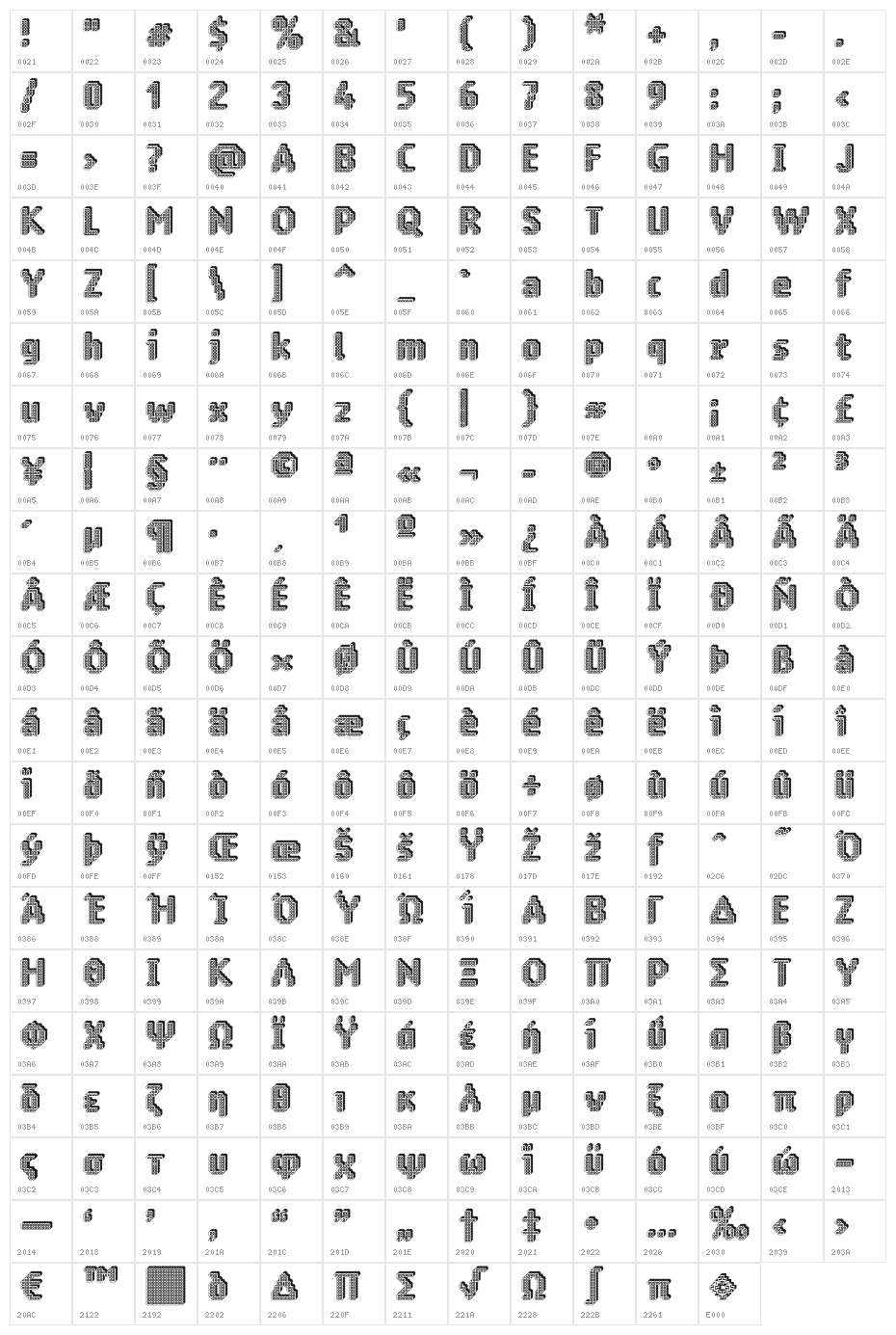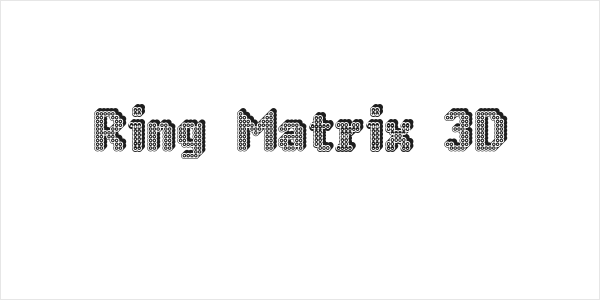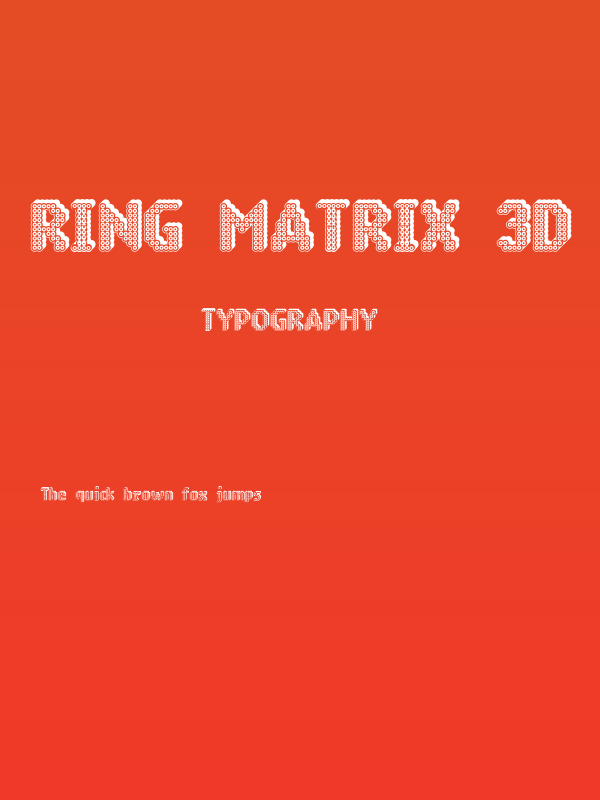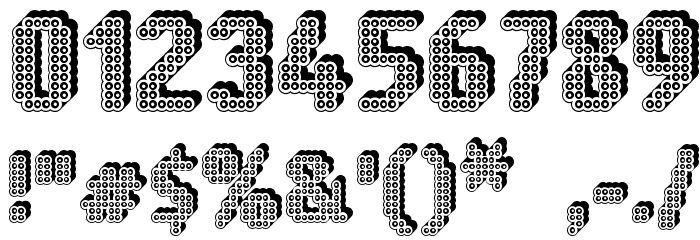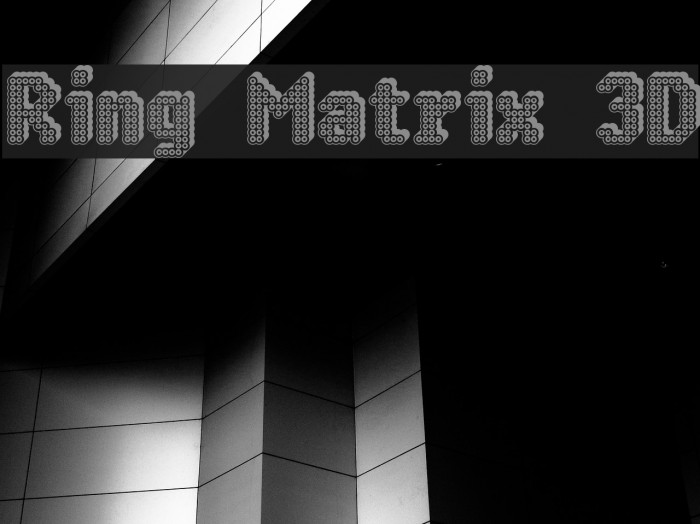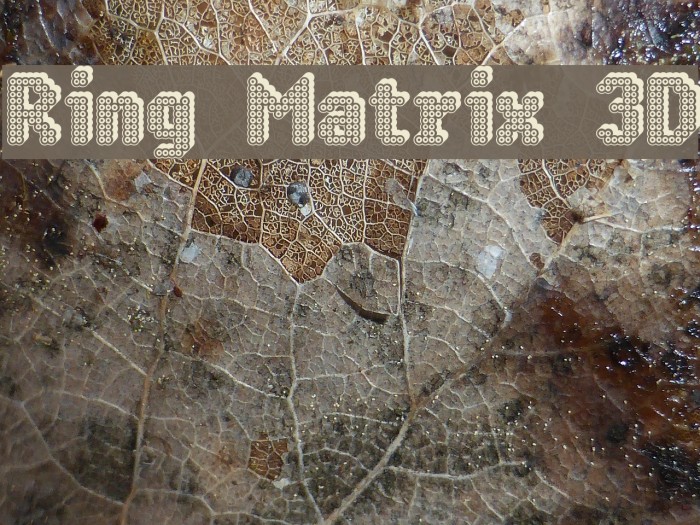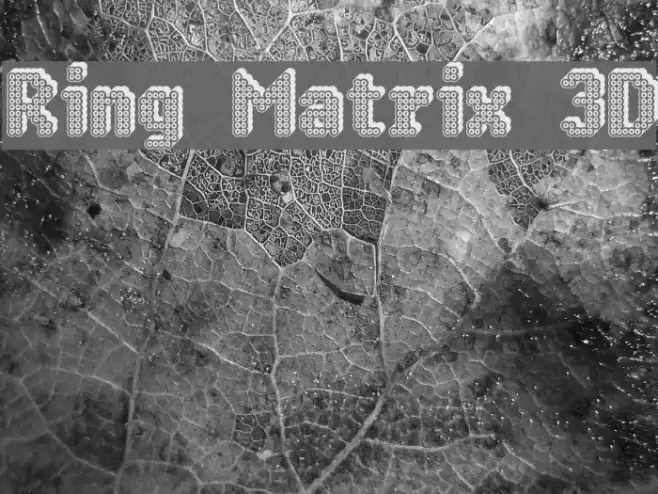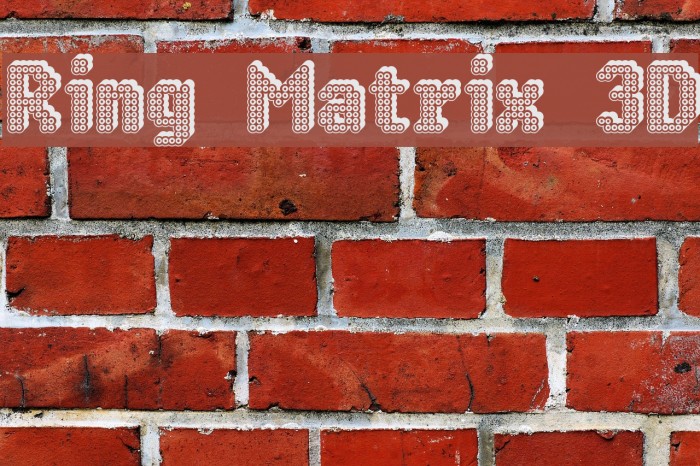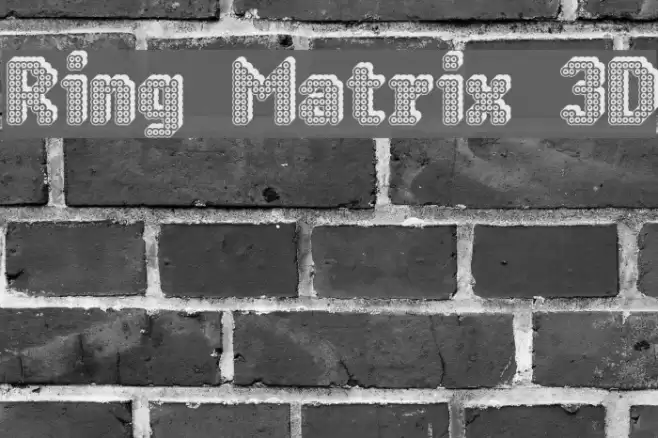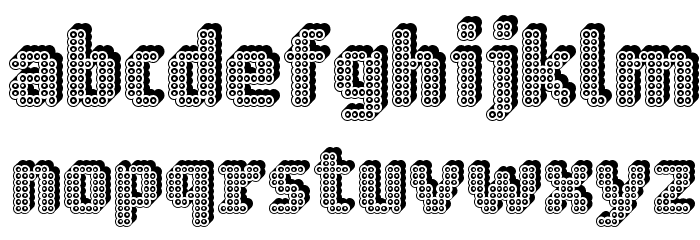
Ring Matrix 3D Font
| Caso d'uso | Logos, Posters, Digital Art |
| Progetti proposti | Ideal for creative projects such as posters, logos, and digital art where a striking and modern appearance is desired. |